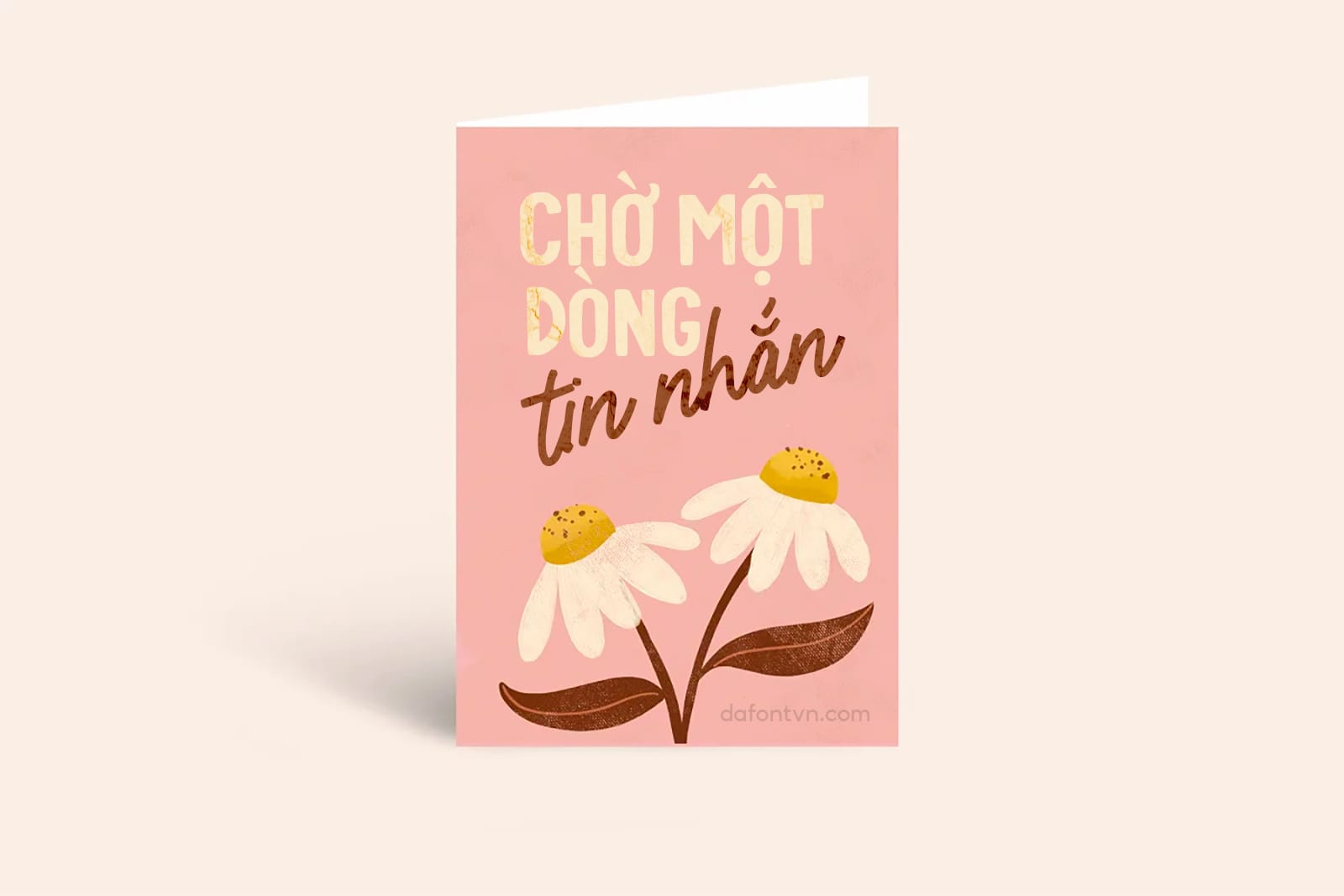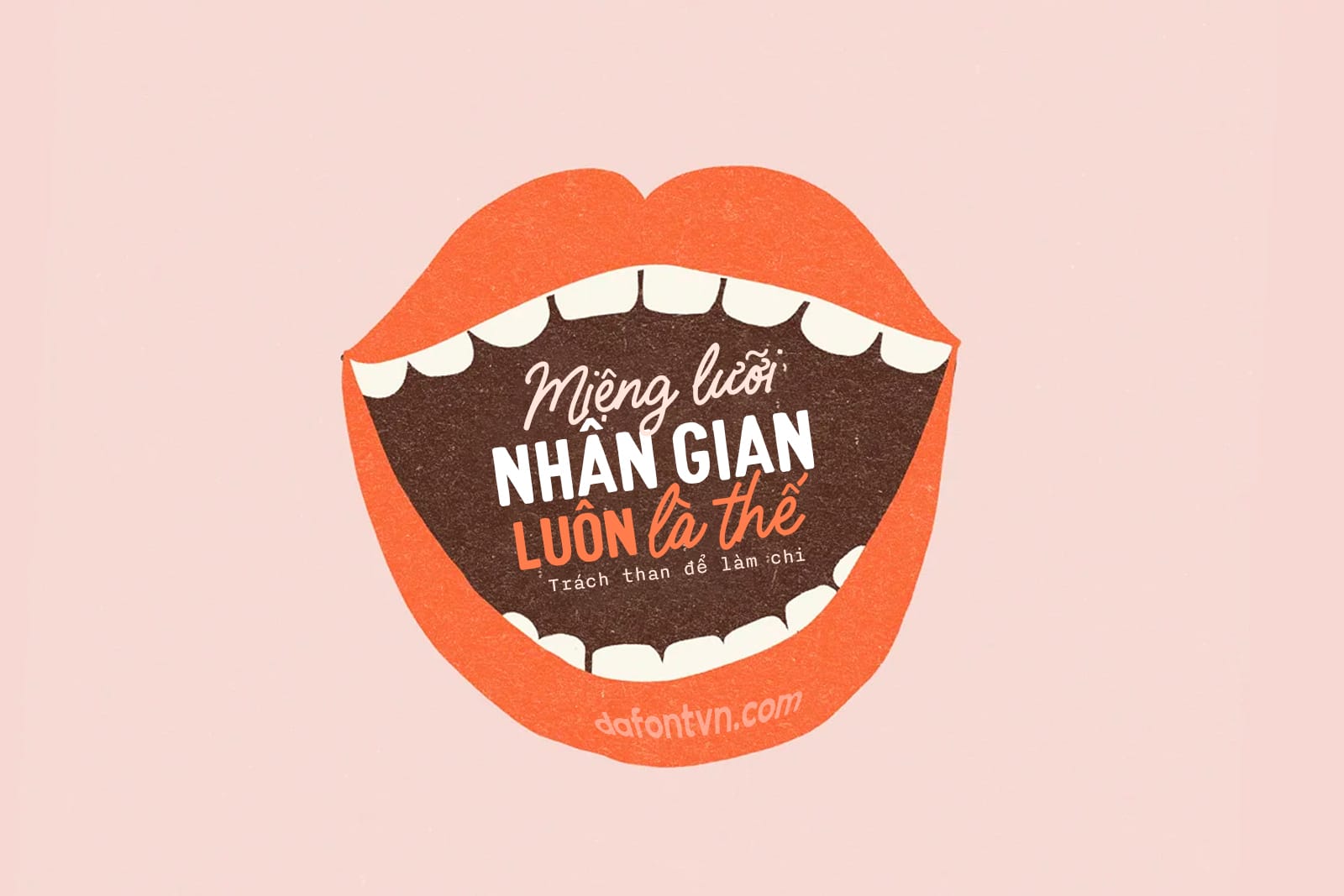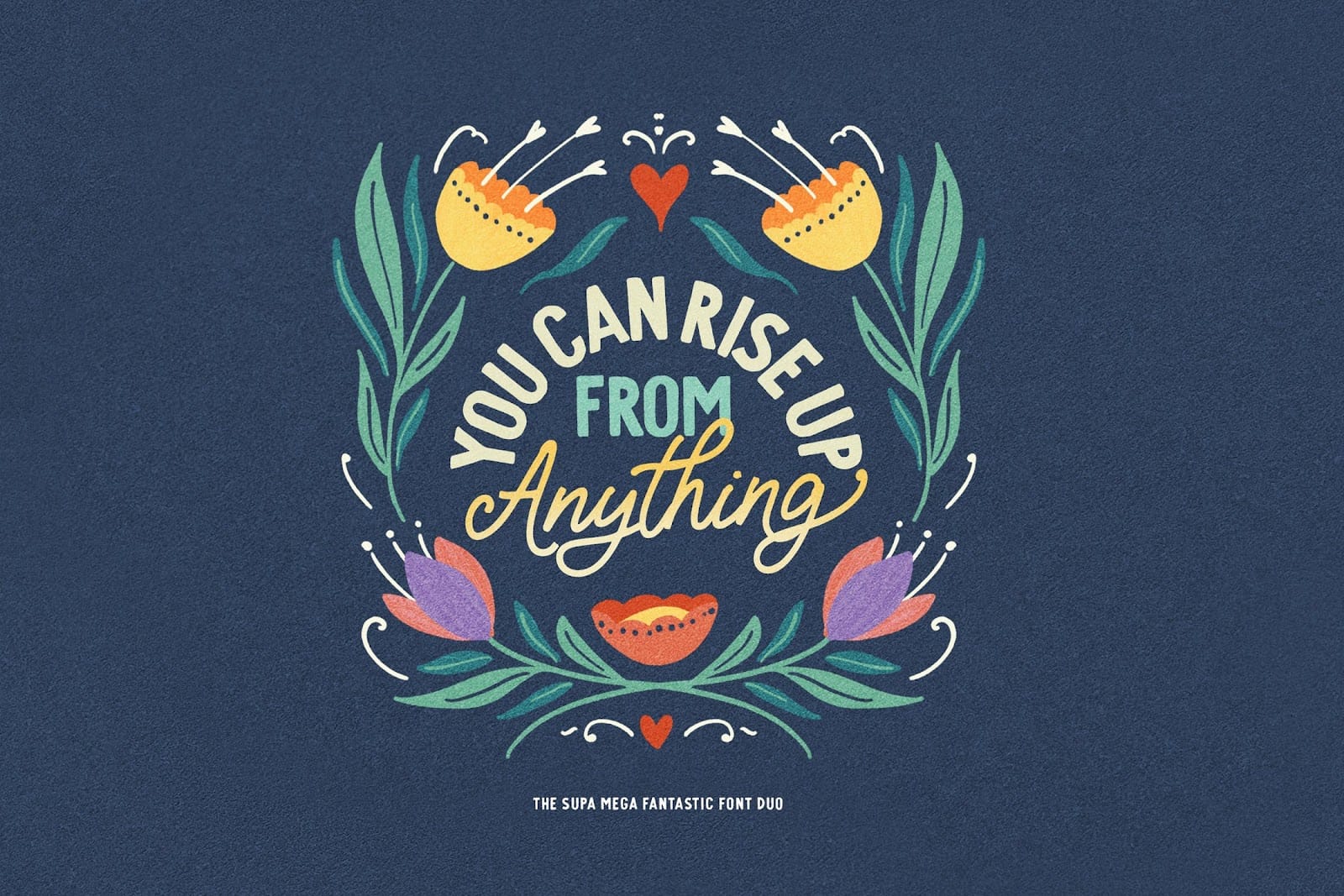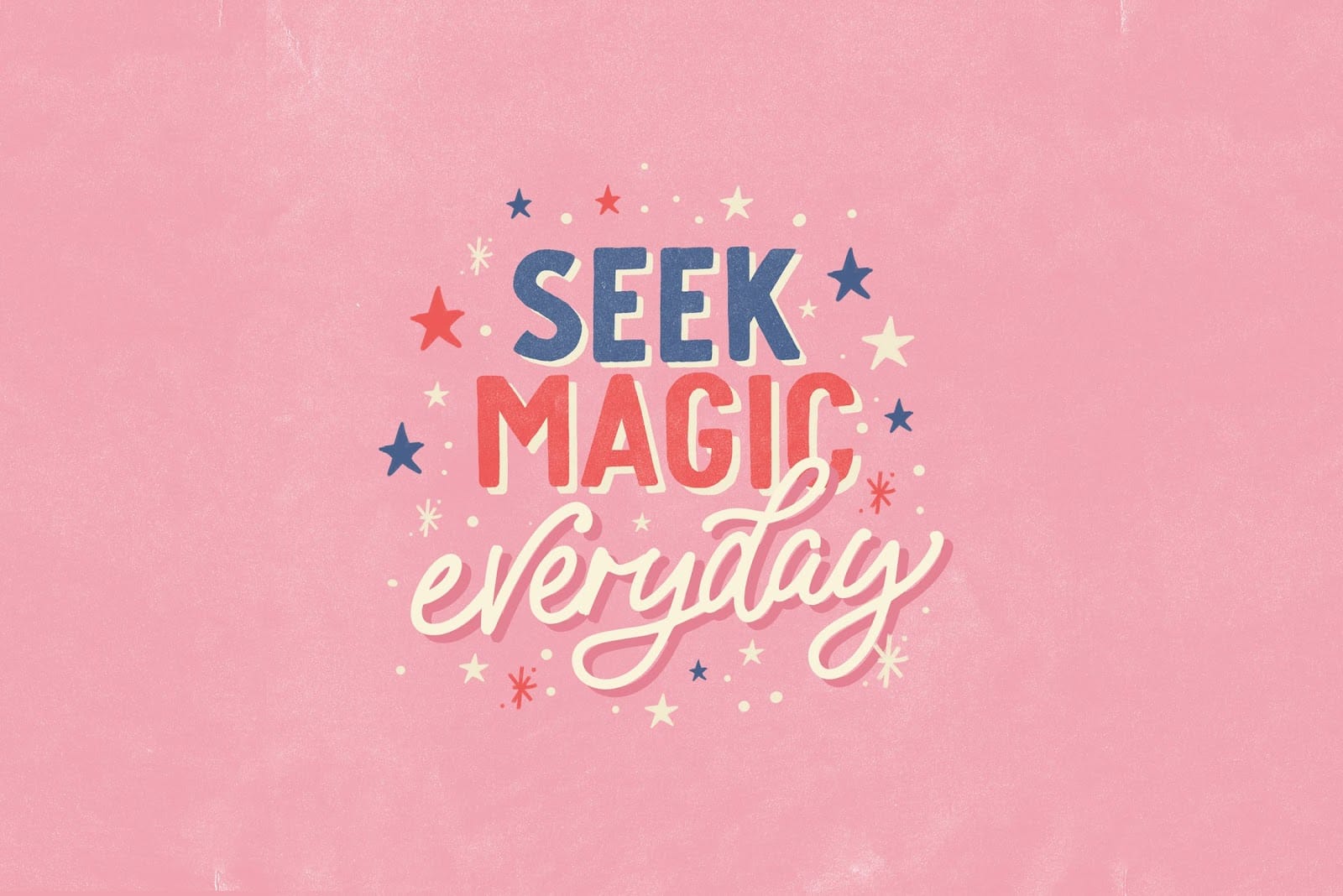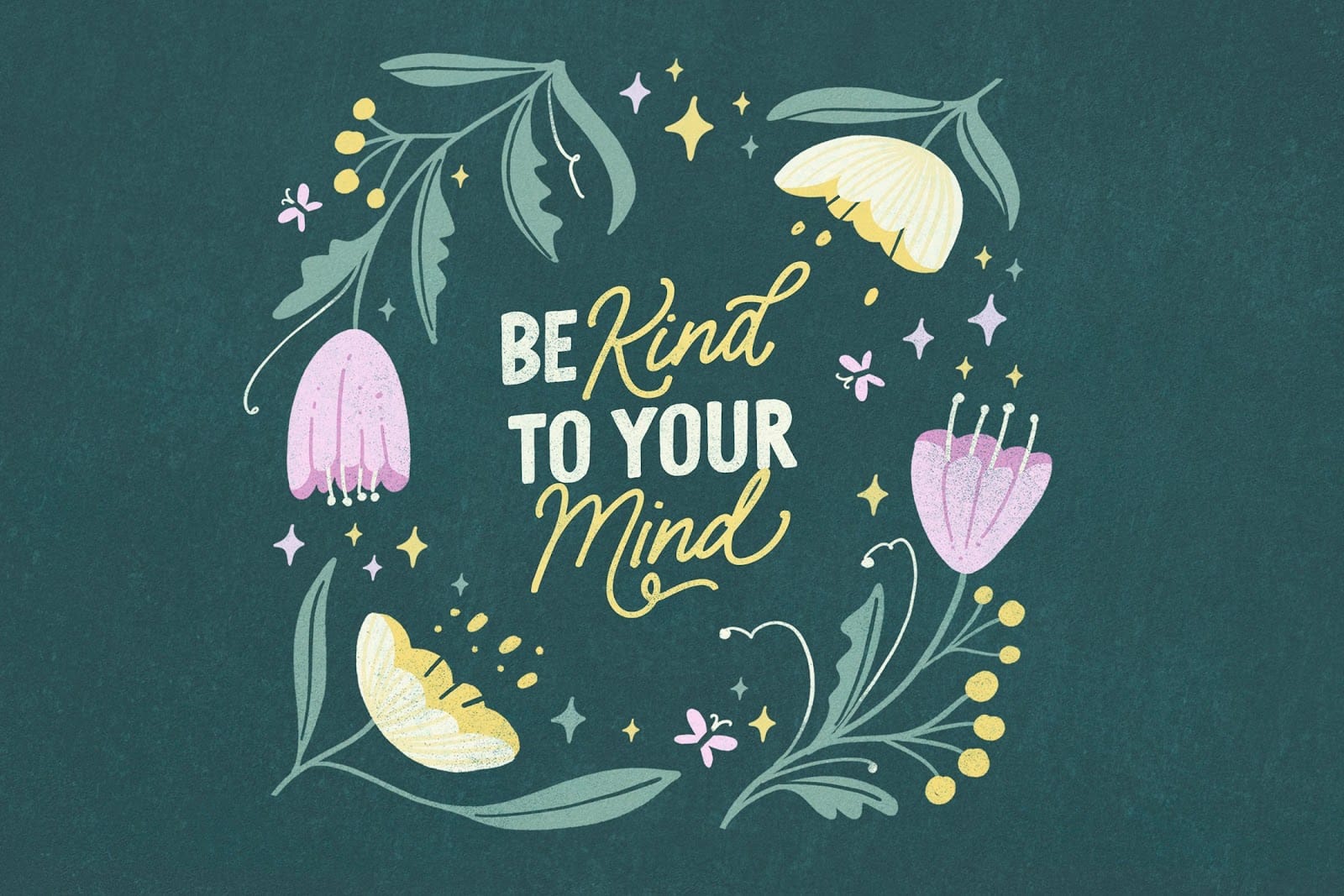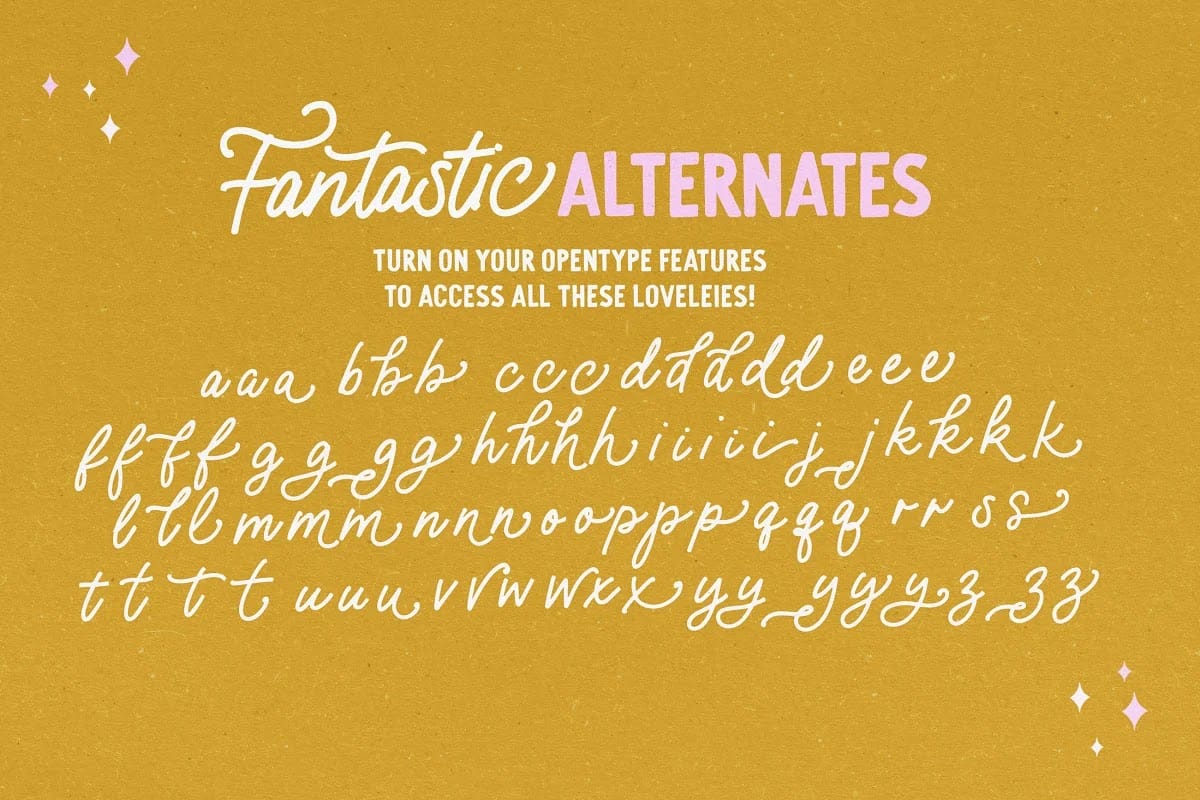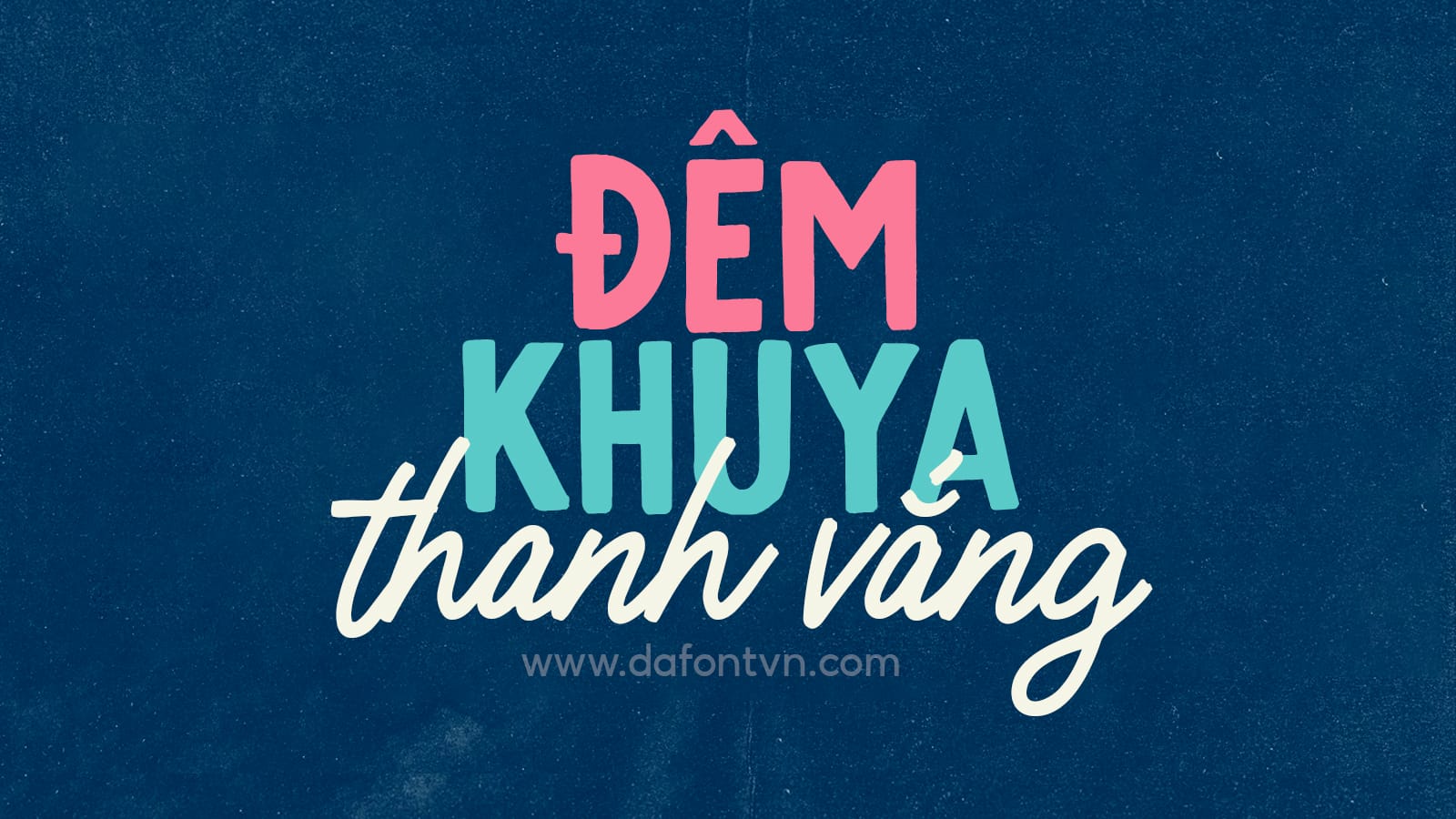
Supa Mega Fantastic Font Việt Hóa bao gồm 3 font với phong cấch vui tươi và chỉn chu. Supa Mega Fantastic Script đi kèm với vô số ký tự thay thế Opentype, để thêm sự tinh tế lạ mắt cho các thiết kế của bạn.
Tất cả các ký tự viết hoa và tất cả ký tự viết thường đều có alternate để bạn lựa chọn sao cho phù hợp nhất cho từng thiết kế của bạn. Script có 2 kiểu, mỗi kiểu sẽ có một chút khác nhau với 1 kiểu mỏng và 1 kiểu thông thường.
Font phù hợp để xây dựng thương hiệu với kiểu chữ vui tươi, thiệp mời, quote, thiết kế bao bì… Để tận dụng tối đa tất cả các chữ cái phụ bạn hãy sử dụng tính năng Opentype nhé. Font việt hóa đầy đủ bởi iCiel, mình đã kerning và tối ưu lại.